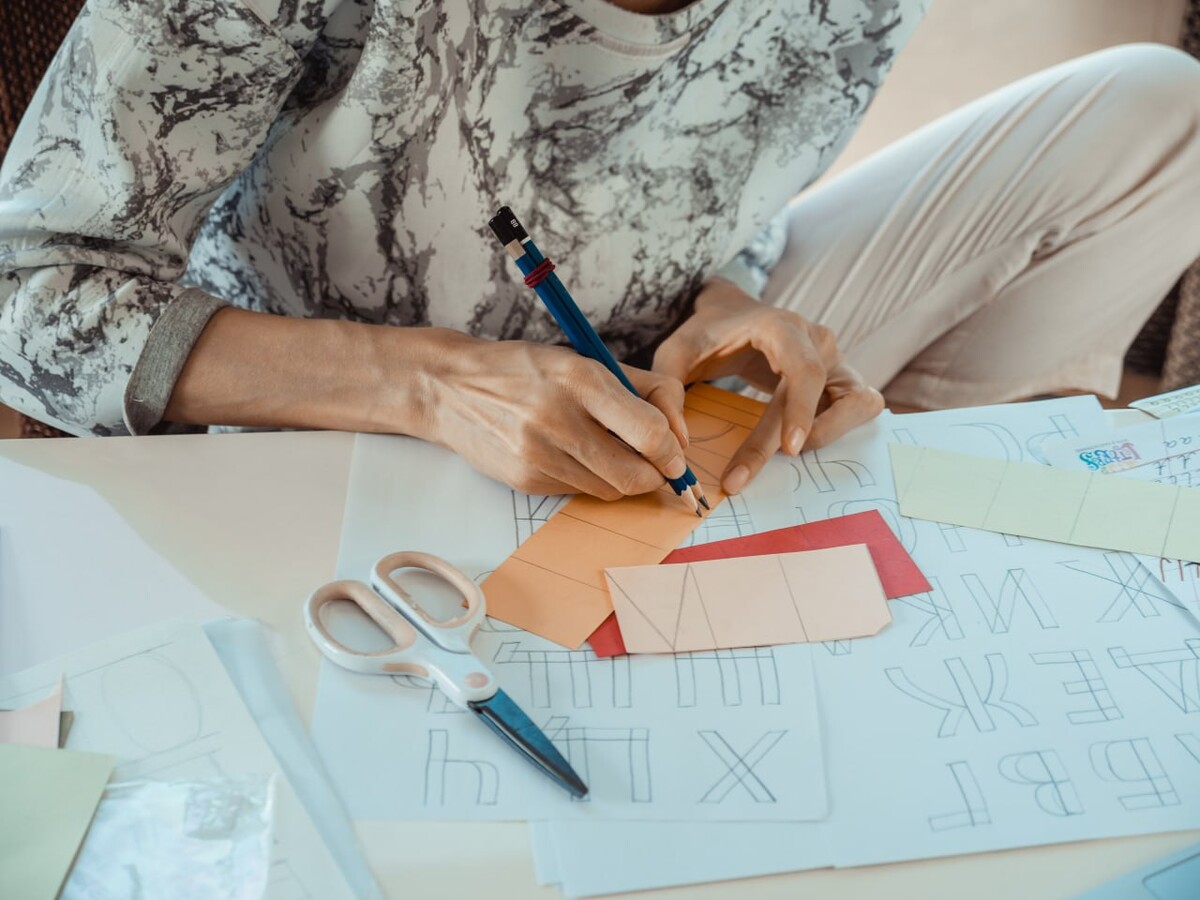
Когда мир отражается иначе: письмо для левшей и подготовка к школе
Как мама и педагог, я часто вижу, как тревожатся родители левшей. Кажется, что такому ребёнку в разы сложнее вписаться в школьные стандарты. В нашем сообществе мы рассматриваем обучение письму для детей не как муштру, а как естественное движение, «дыхание» руки. И для левши постановка руки для письма работает так же, как и для правши, но со своими нюансами. Если заметить их вовремя, в будущем не потребуется исправление почерка.
Как правильно держать ручку без боли: правильный захват ручки ребёнком и борьба с зажимом
Главная трудность левши — не в самой руке, а в том, как он пытается адаптироваться к «праворукому» инструменту. Мы часто видим, как ребёнок-левша сжимает ручку в кулачке или закидывает средний палец сверху, создавая «замок». Это формирует неправильное давление ручки при письме и приводит к сильному напряжению. На видео моих учеников-левшей заметно: рука устаёт уже через 5 минут, плечо поднимается, а пальцы белеют от зажима.
Вместо того чтобы заставлять «писать правильно», мы даём левше опыт расслабления и развиваем мелкую моторику для письма. Первое, что мы делаем, — меняем инструмент. Брашпен или аквабраш на уроках каллиграфии помогают ребёнку почувствовать лёгкость движения. Если рука зажата, письмо превращается в каторгу. Наша задача — перевести его в траекторию успеха, где движение идёт от локтя и кисти, а не от судорожного сжатия пальцев.
Ребёнок зеркально пишет буквы: разбираем букву «О» и всю овальную группу, траекторию движений
Левши часто интуитивно выбирают неверное направление движений — например, зеркально пишут буквы или выводят овалы по часовой стрелке. Такое реверсивное движение может казаться удобным в моменте, но в будущем «ломает» письмо. Если буква «О» и вся овальная группа (О, А, Ю, Д) пишется не в ту сторону, ребёнок теряет скорость, тратит ресурс на постоянное обдумывание движений и не может перейти к плавному соединению букв.
Мы используем специальные игровые упражнения для развития почерка и учим левшей единому алгоритму движений — против часовой стрелки. Как только ребёнок осознаёт эту логику через работу с крупными формами и кистью, мозг перестаёт тратить ресурс на «выдумывание» каждой буквы заново, и письмо становится более плавным и уверенным. Так формируется красивый почерк без слёз.
Как улучшить почерк левши: наблюдения из практики
Переучивать левшей нельзя — это против природы ребёнка.
Праворуким и леворуким детям письмо даётся одинаково сложно: большую роль играет физическое и нейрофизиологическое развитие. Дети, которые с раннего возраста занимались гимнастикой и спортом, лучше владеют своим телом, быстрее «дружат» голову и руку и легче осваивают письмо.
Левши могут писать красиво. Красота и точность линий достигаются регулярной практикой, как и у всех. Среди профессиональных каллиграфов много левшей.
Методика «Игра в каллиграфию» и её принцип «сначала интерес и ощущение успеха, потом техника» одинаково хорошо работают и для левшей, и для правшей. Мы не начинаем с жёсткой коррекции посадки и позы, а выстраиваем процесс так, чтобы ребёнку было интересно. Тогда тренировки в прописях со временем становятся естественной частью процесса, а не наказанием.
Полезная практика для детей и взрослых — амбидекстрия, умение использовать обе руки. Она развивает координацию и улучшает взаимодействие мозга и тела.
Важно помнить: большинство левшей не испытывают серьёзных трудностей с письмом, если на них не давят. Они находят удобное положение листа и инструмента через эксперимент. Левша — это не проблема, а другой способ взаимодействия с пространством, который при правильном подходе даёт отличные результаты и позволяет улучшить почерк с удовольствием.